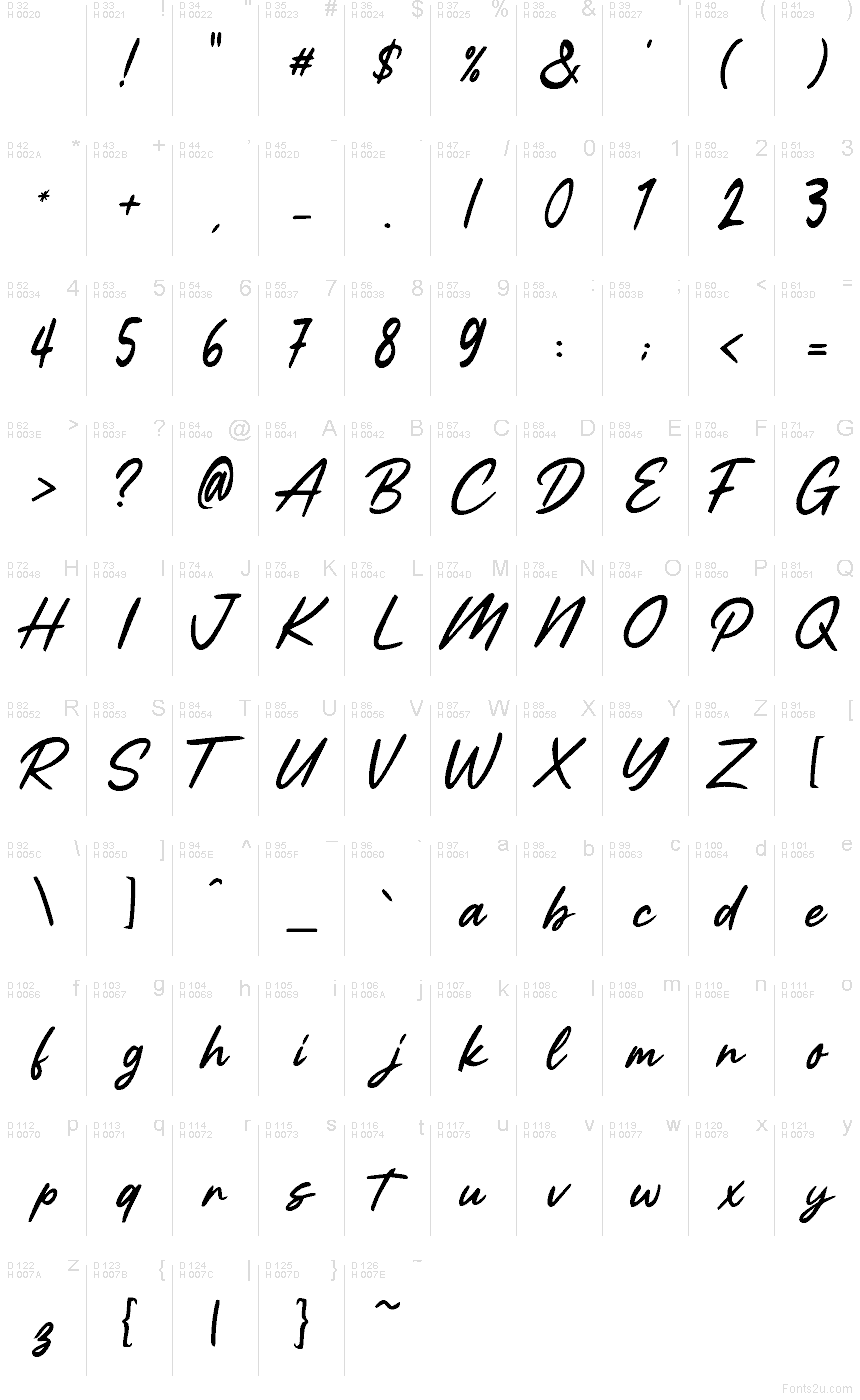
Abstract Spectrum od BlackFridayFont je bezplatné ručně psané písmo s rychlým rytmem připomínajícím tah štětcem a dlouhými diagonálními tahy, které udržují písmena v pohybu. Tvary působí spíše skicovitě než uhlazeně, takže písmo působí jako rychlý podpis, a nikoliv jako formální kaligrafický styl.
Tato energie se hodí na obaly alb, streetwearovou grafiku, plakátové nadpisy, citáty na sociální sítě nebo návrhy log, které potřebují neformální osobní značku. Zametavé diagonály a ostré změny směru dodávají krátkým titulkům na obalech i eventovému brandingu bezprostřední vzhled psaný rukou.